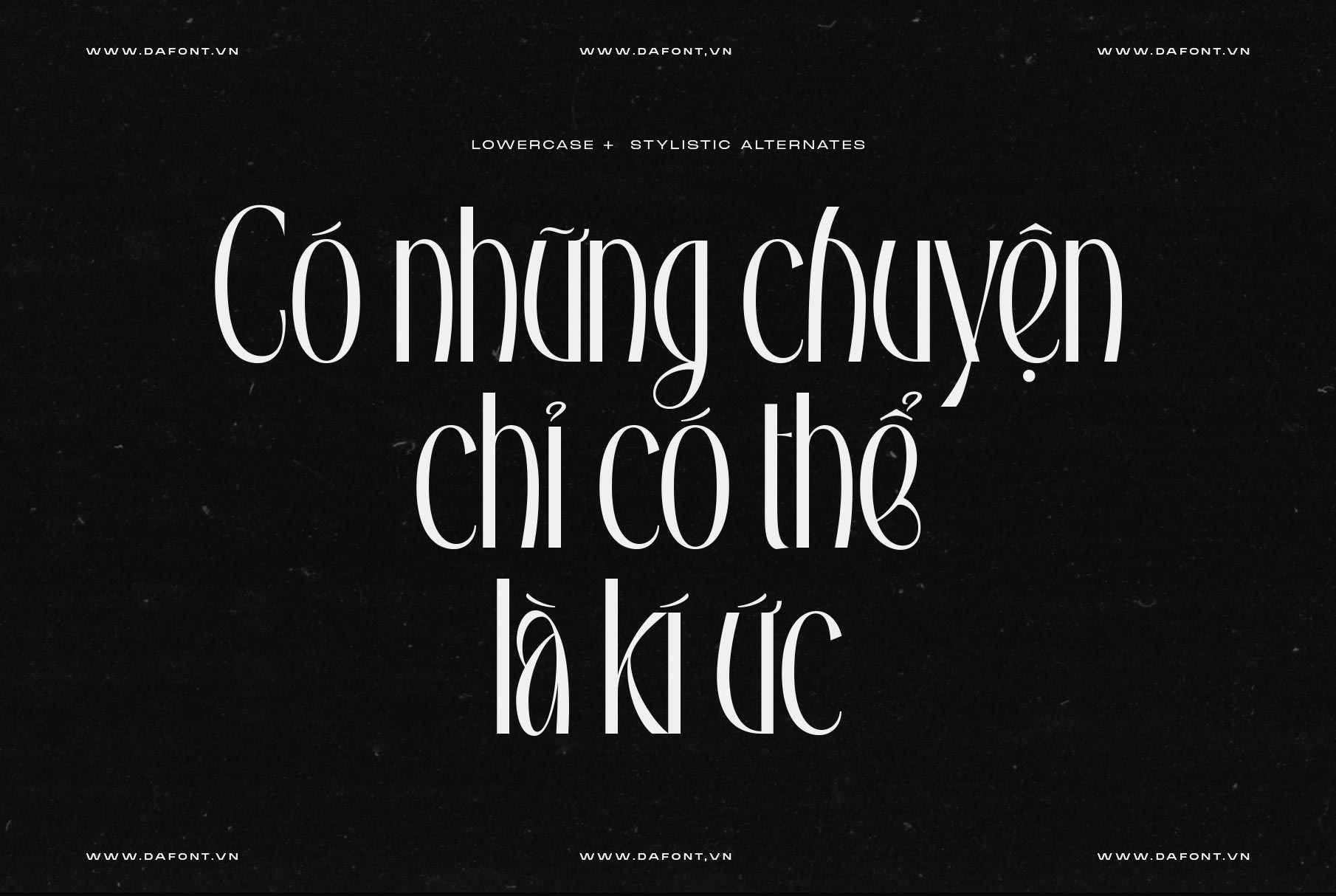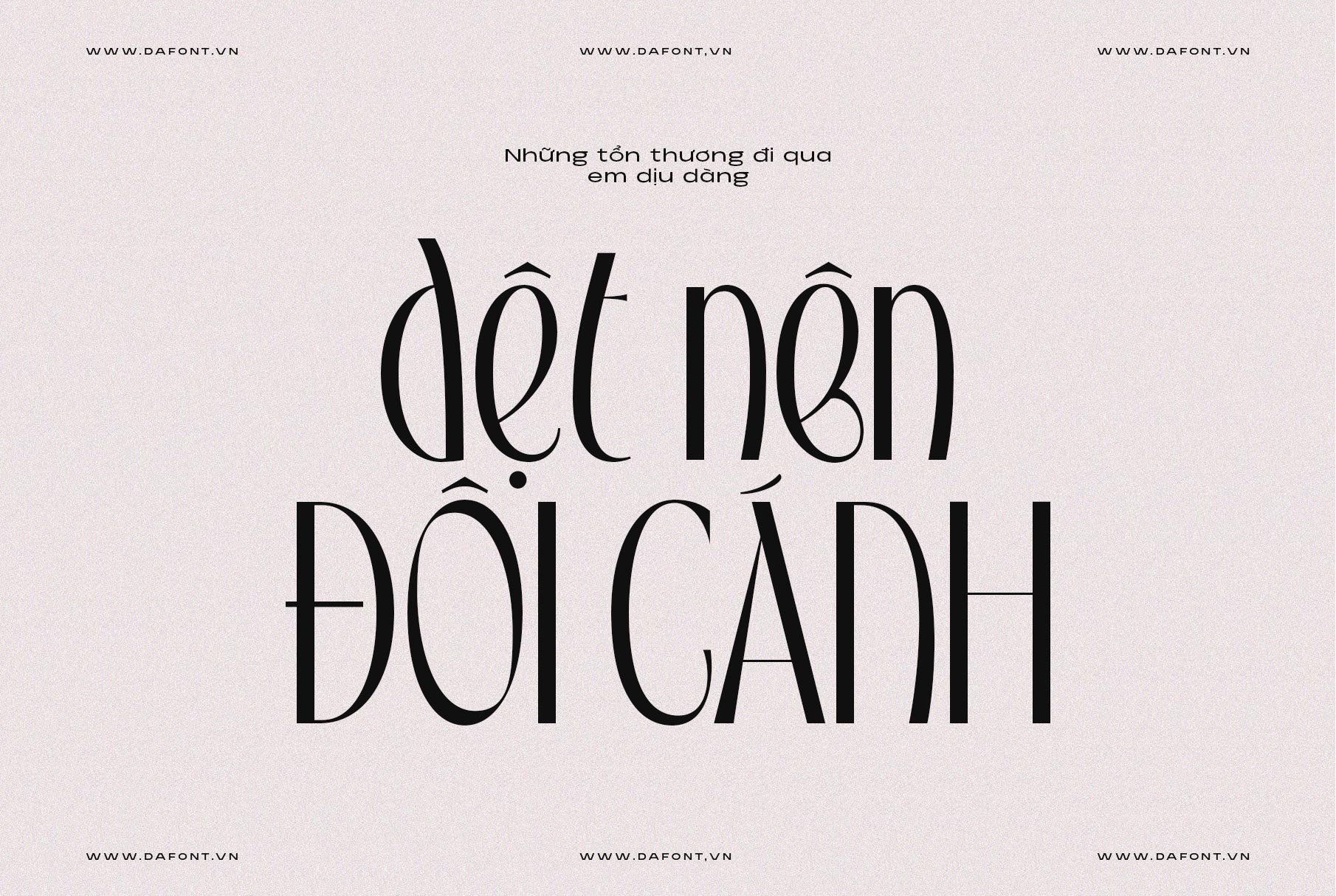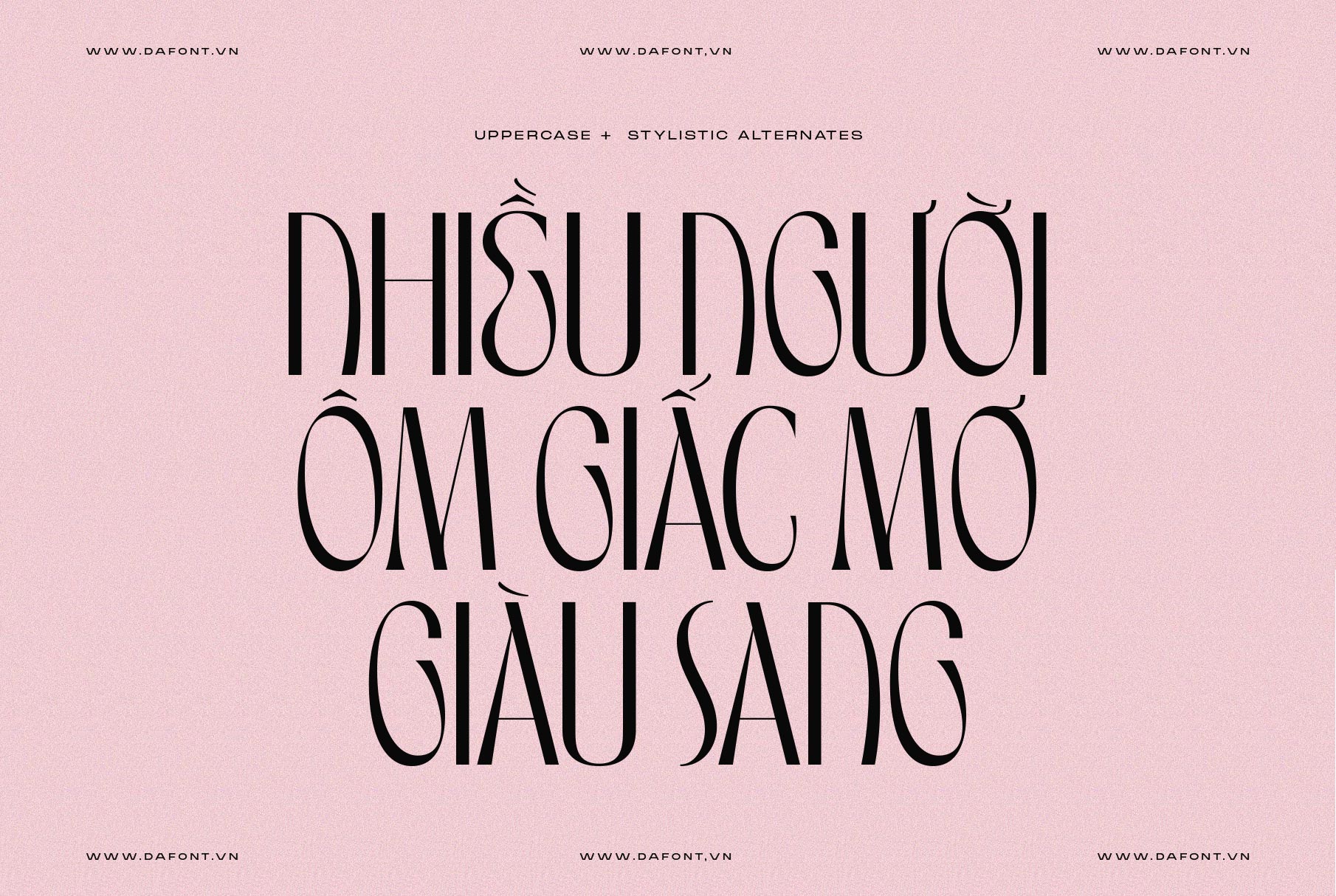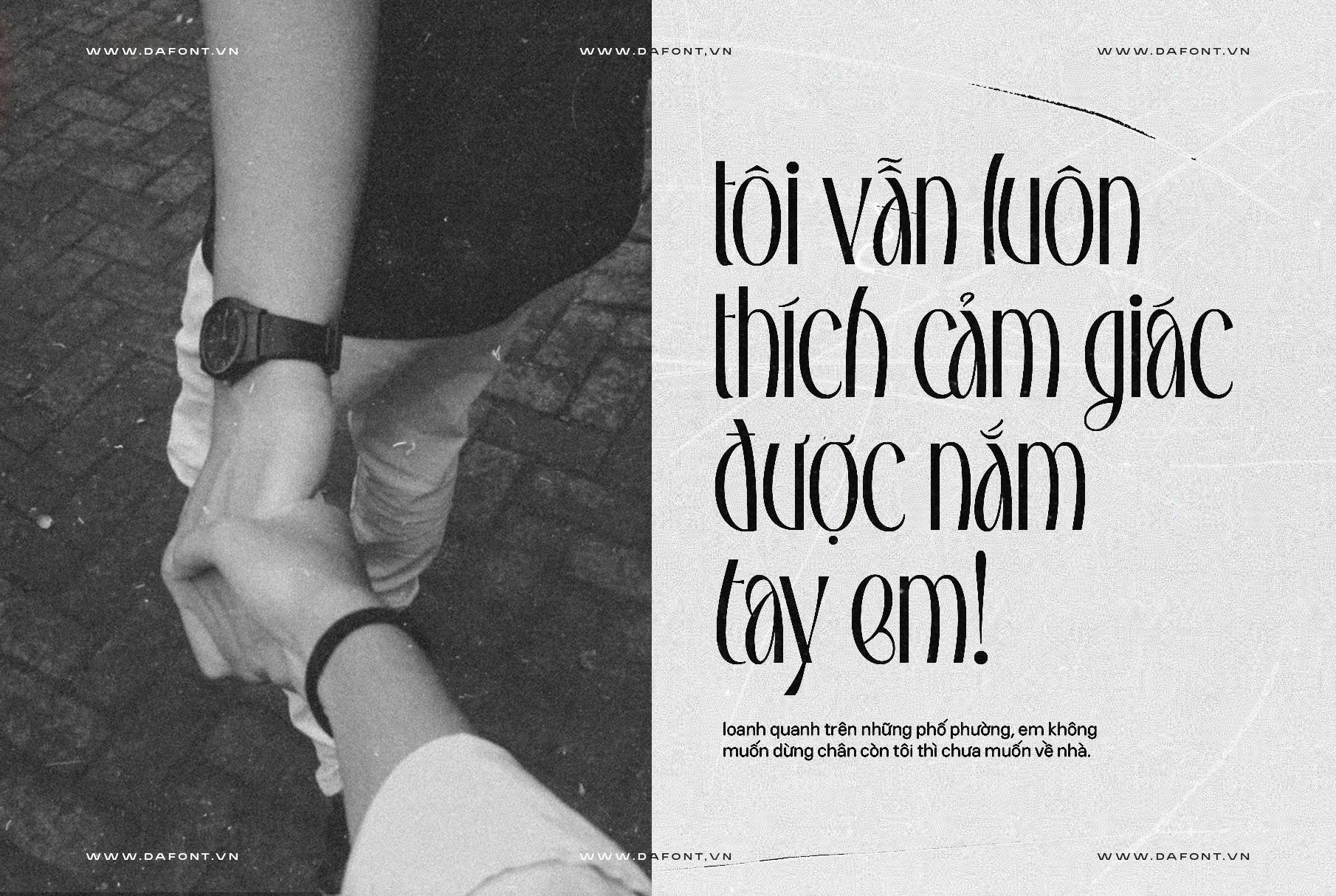
DFVN TAN – FAIRVIEW
Font chữ đẹp mắt lấy cảm hứng từ Art Deco
Nếu bạn đang tìm kiếm một phông chữ đẳng cấp với phong cách Art Deco, hãy khám phá TAN – FAIRVIEW font. Được thiết kế với cảm hứng từ phong cách Art Deco cổ điển, TAN – FAIRVIEW là lựa chọn hoàn hảo cho các dự án sáng tạo cần sự thanh lịch và sang trọng. Với các đặc điểm nổi bật như thanh mảnh, đơn giản và nét hiện đại, phông chữ này chắc chắn sẽ thu hút sự chú ý của người xem ngay từ cái nhìn đầu tiên.
Đặc điểm nổi bật TAN – FAIRVIEW
TAN – FAIRVIEW font không chỉ đẹp mà còn linh hoạt trong cách sử dụng. Phông chữ này sở hữu các đường nét mảnh mai và gọn gàng, tạo nên vẻ thanh thoát nhưng không kém phần nổi bật. Dưới đây là một số điểm mạnh của TAN – FAIRVIEW font:
• Phong cách Art Deco: Lấy cảm hứng từ nghệ thuật Art Deco nổi tiếng của những năm 1920, phông chữ này mang lại cảm giác cổ điển nhưng vẫn hợp thời.
• Thiết kế đơn giản và hiện đại: Mặc dù dựa trên phong cách cổ điển, TAN – FAIRVIEW vẫn có một chút biến tấu hiện đại, tạo sự hài hòa giữa quá khứ và hiện tại.
• Lý tưởng cho các dự án hiển thị: TAN – FAIRVIEW là một phông chữ hiển thị phù hợp cho các tiêu đề, poster, bìa sách, hoặc các sản phẩm sáng tạo đòi hỏi sự nổi bật và ấn tượng.
Lý do bạn nên chọn TAN – FAIRVIEW
Sử dụng TAN – FAIRVIEW font không chỉ giúp bạn có được một thiết kế đẹp mà còn mang đến sự khác biệt cho thương hiệu của bạn. Nếu bạn muốn một phông chữ thể hiện phong cách hiện đại nhưng vẫn tôn vinh nét cổ điển của art deco, TAN – FAIRVIEW chính là sự lựa chọn tuyệt vời. Bằng cách chọn TAN – FAIRVIEW font cho các dự án thiết kế, bạn không chỉ đang chọn một phông chữ đẹp mắt mà còn mang lại phong cách và cá tính riêng biệt cho sản phẩm của mình.